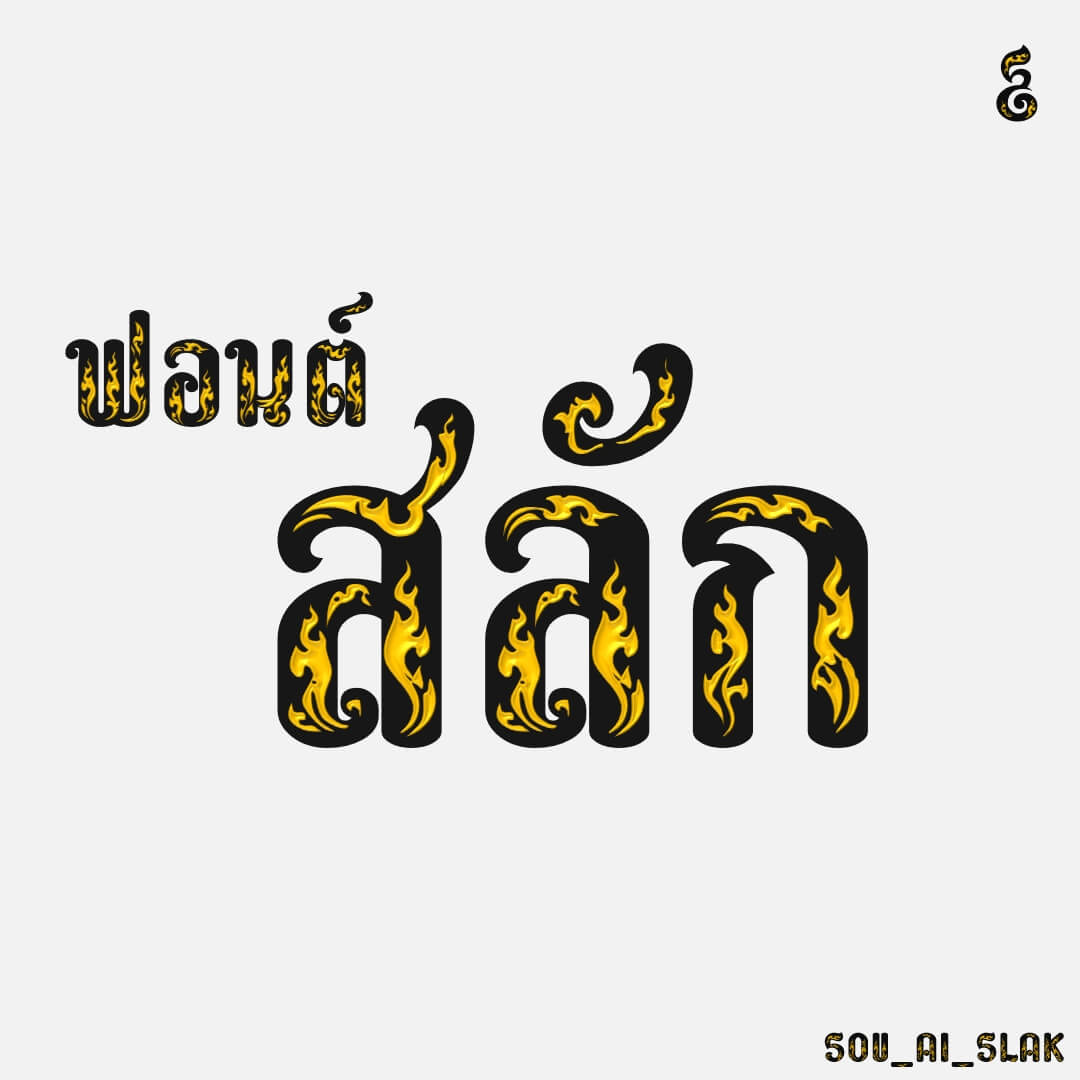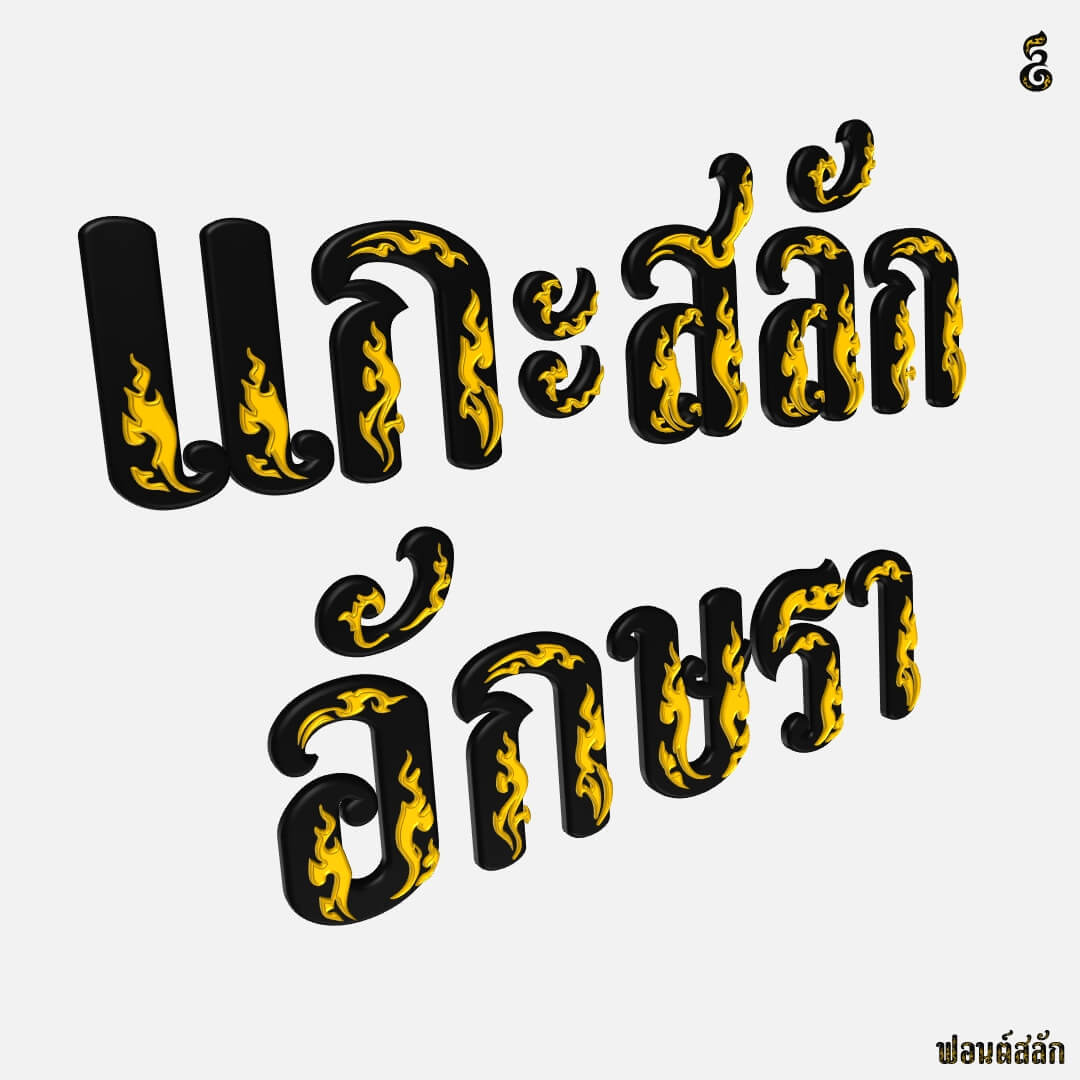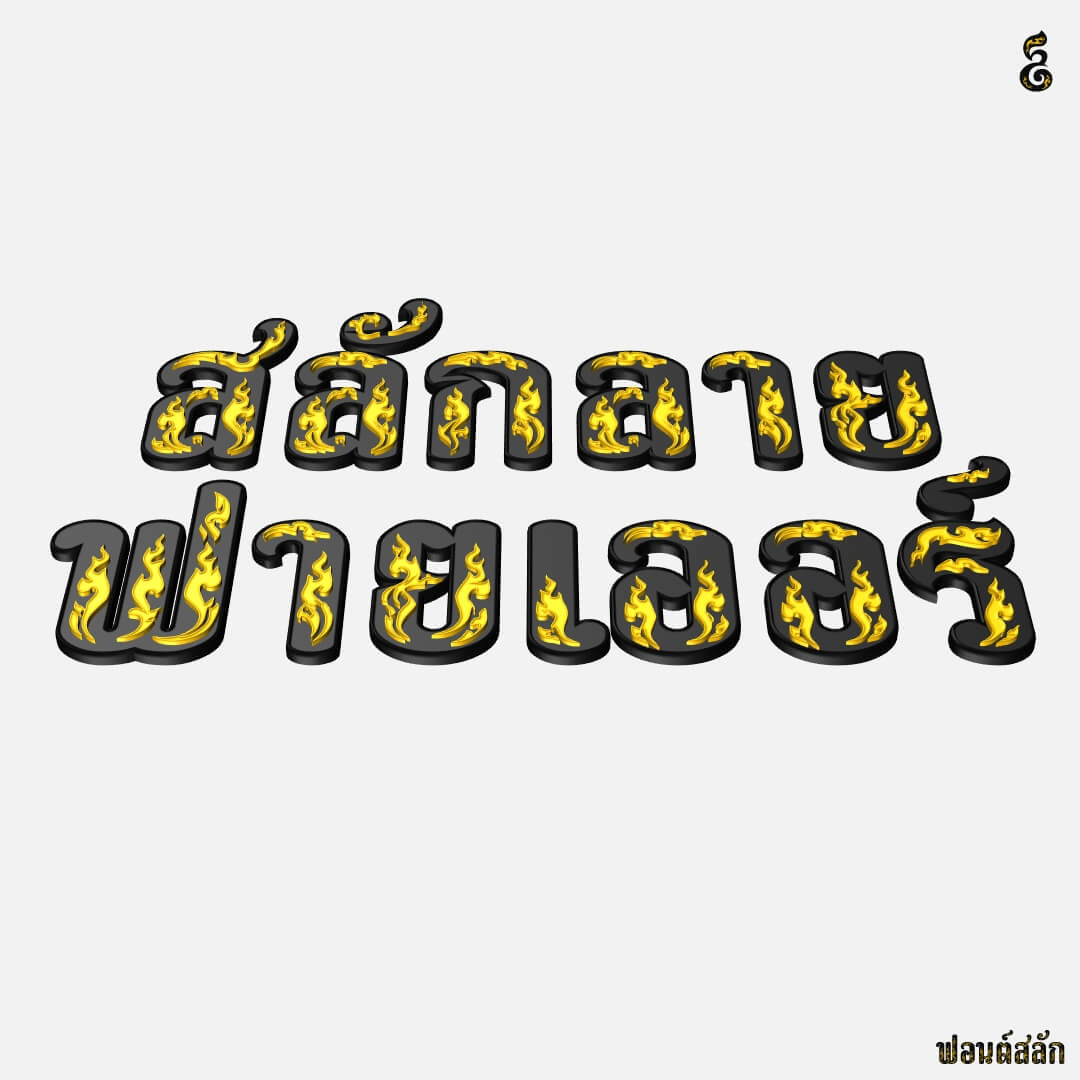
สลัก – ทดลองให้ AI ออกแบบลายบนฟอนต์ของเราที่มีความกว้างของเส้นอักษร …ฟอนต์ธนบุรี (SOV_ThonBuri) เพื่อให้ได้ลายขนาดใหญ่ สำหรับทำเป็น layer font ซ้อนอยู่บนฟอนต์เดิม สามารถใส่ effect นูน บุ๋ม คล้ายการแกะสลัก
เวลาใช้งาน พิมพ์ฟอนต์ธนบุรีก่อน จากนั้นทำ layer ใหม่ ซ้อนขึ้นมา แล้วค่อยเปลี่ยนเป็นฟอนต์ตัวนี้ ก่อนตกแต่งต่อไป
สลัก (SOV_AI_Slak)